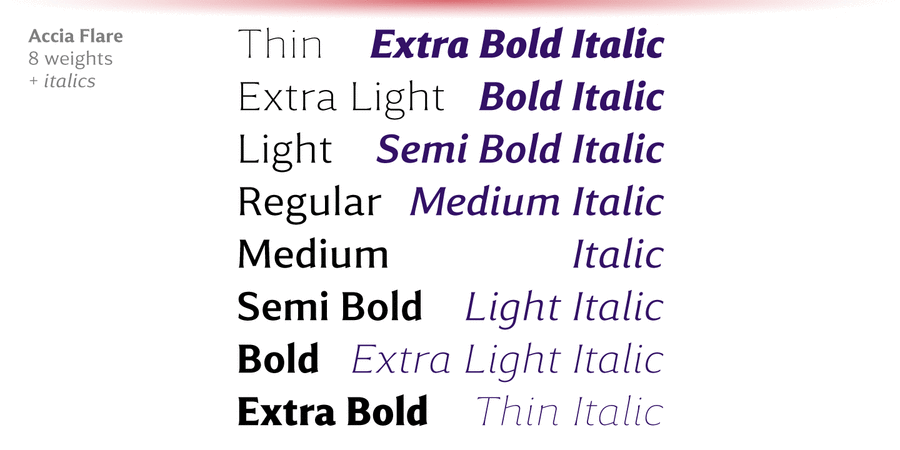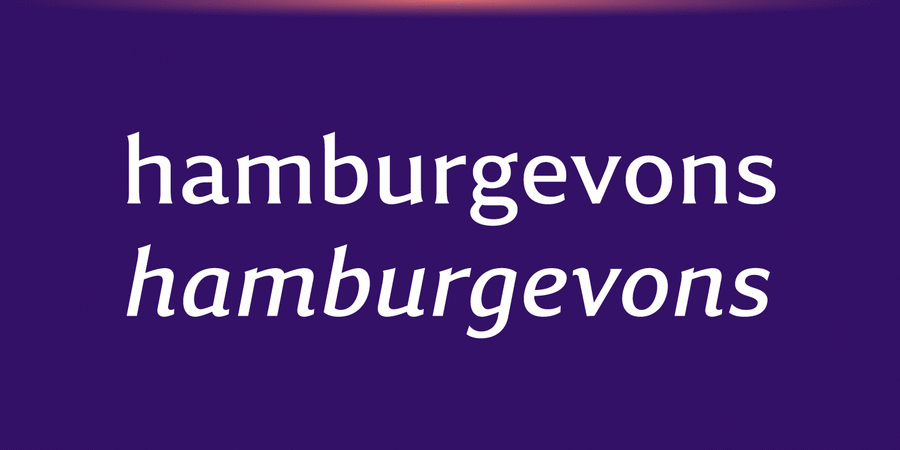
Опис гарнітури Accia Flare – елегантний гліптальний шрифт з великою висотою рядкових і низьким контрастом. Його тонкі вигини створять ніжний, але помітний образ у дизайні упаковки. Шрифтове сімейство містить 8 накреслень від Thin до Extra Bold з відповідними курсивами. Кожне накреслення має велику мовну підтримку, включно з кирилицею, а також численні функції OpenType: капітель, лігатури, кілька наборів цифр, пунктуація з урахуванням регістру, дроби й індекси. Accia Flare є частиною супергарнітури Accia, куди входять п'ять шрифтів, від гротеску до виразної антикви. Це дає вам можливість проектувати максимально складні серії продукції або інформаційні системи. Система Accia складається з Accia Sans, Accia Flare, Accia Piano, Accia Moderato і Accia Forte. Гарнітуру розробив Андрій Константинов в студії Mint Type у 2021 році.